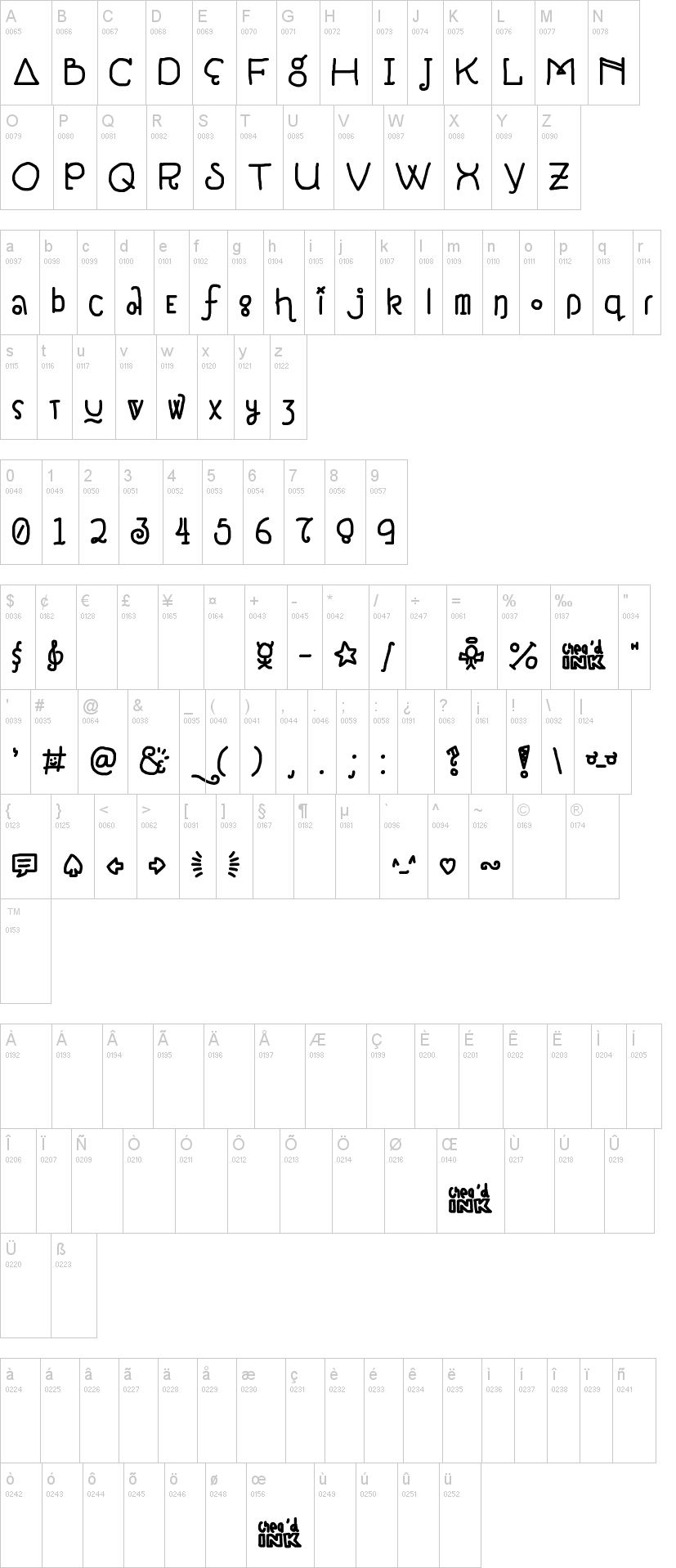
Notepads & Roleplay
? Notepads & Roleplay 是一款非常流行的日式字体,它有着简洁的设计,拥有优美的曲线,以及清晰的细节。它的特点是自然的笔画,简洁的外观,以及非常柔和的线条。它适合用于日常文字排版,也可以用于角色扮演游戏的文字。
Notepads & Roleplay是一款非常不错的手写艺术字体,具有很好的视觉感,适合于文化类的宣传设计、商业类品牌的广告和产品包装设计以及个性化文字排版等较多场景。
Notepads & Roleplay字符映射图